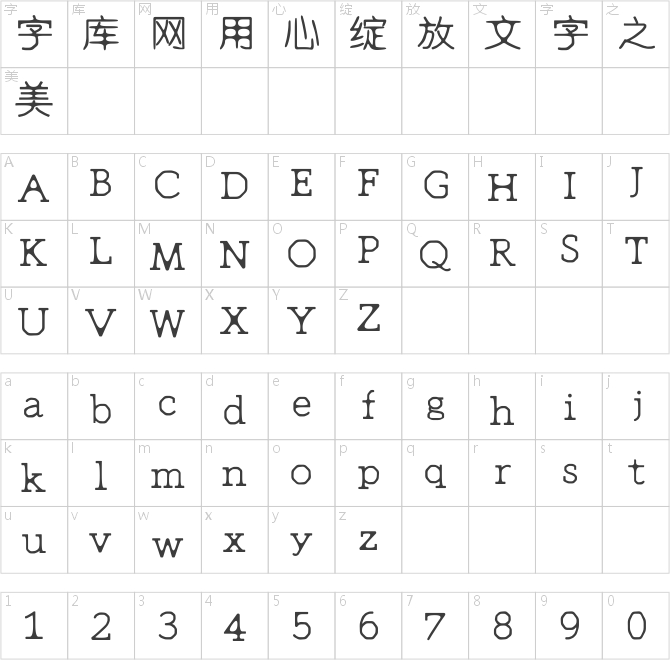
字體名稱: 【變形】花節(jié)體
【變形】花節(jié)體
【變形】花節(jié)體字體字庫是一款讓人賞心悅目、百看不厭的中文字體,適合各類廣告和產(chǎn)品包裝設(shè)計(jì)應(yīng)用,字體大小15.85MB,格式為ttf字體,上傳用戶是釜源貿(mào)易,作者/版權(quán)方為未知